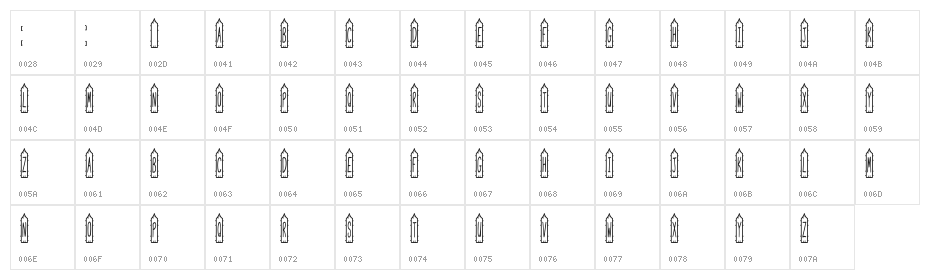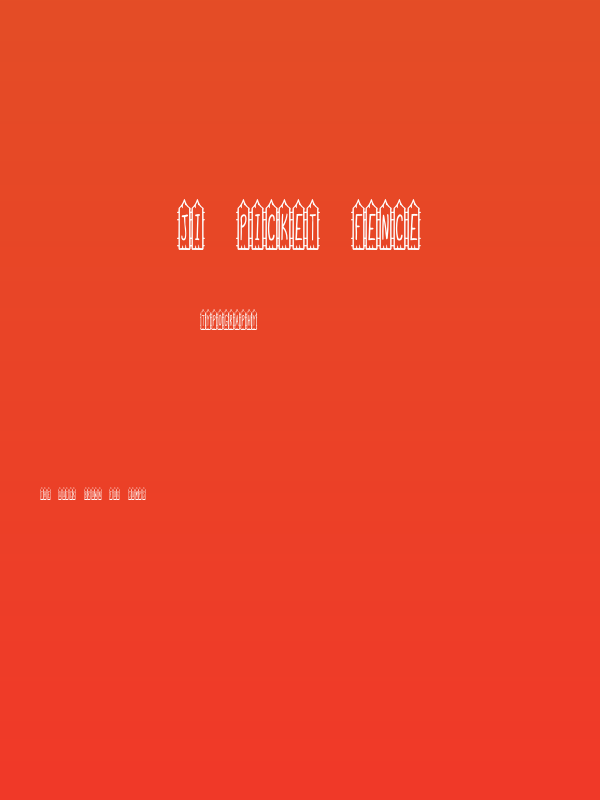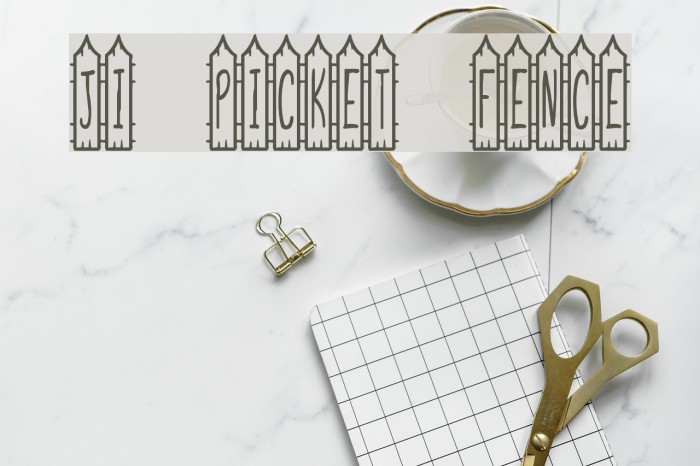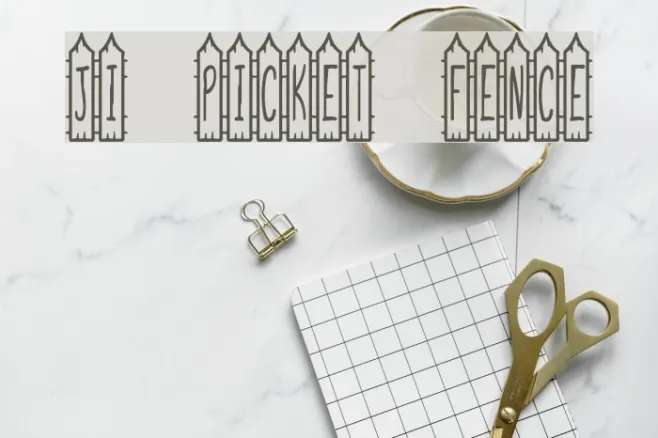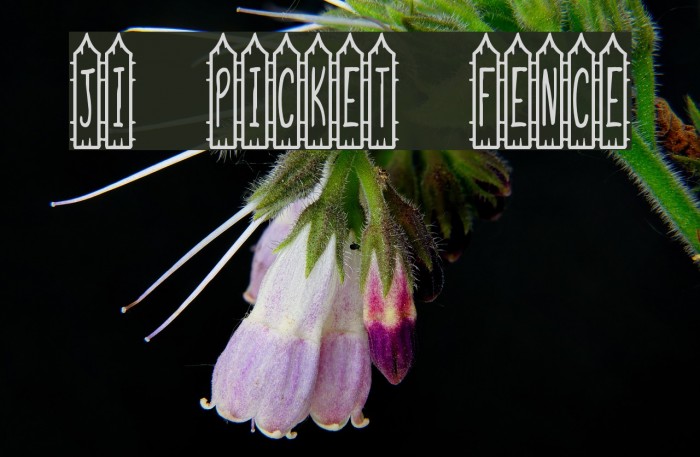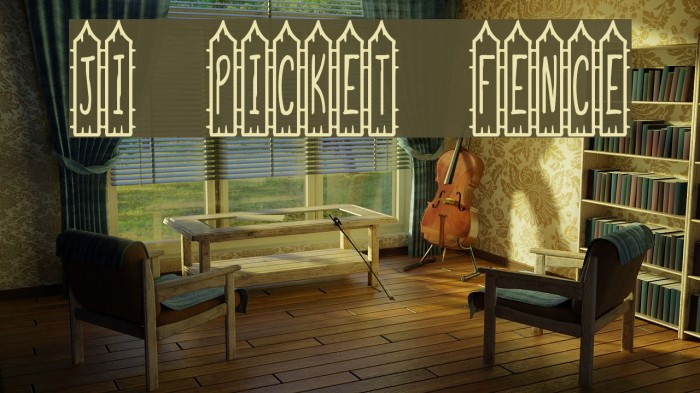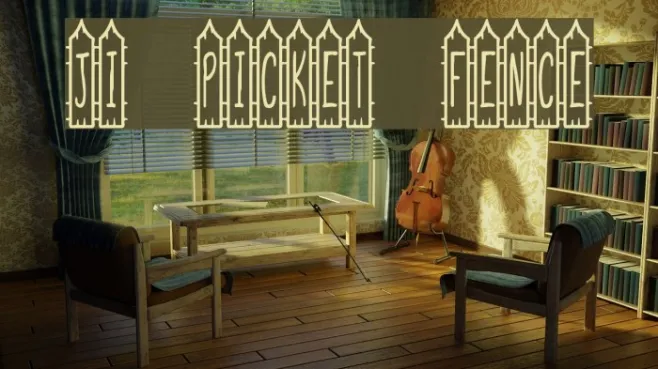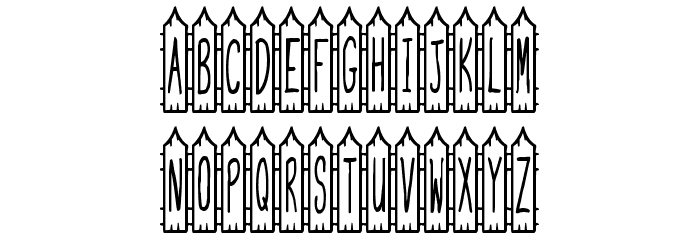
JI Picket Fence Font
| Vorgeschlagene Projekte | Ideal for children's books, playful branding, themed event materials, or any project needing a whimsical touch. |